А какой твой акцидентный шрифт? Виды акциденции — Дизайн на vc.ru
Акцидентные шрифты — не такие, как все. Примерно так звучит определение этой группы шрифтов. Вот только свалить их в одну кучу и успокоится — не наш вариант. Они, как и наборные шрифты, имеют свою классификацию.
Классификация
На первый взгляд классификация декоративных гарнитур крайне не очевидна, обширна и разностороння. Но мы разобрались в ней и, специально для вас, разложили всё по полочкам.
Рукописная акциденция
Здесь всё просто и прозаично и кроется в названии, впрочем, как и в других видах. Шрифты из этой группы тем или иным образом подражают рукописному тексту. При этом такие шрифты не являются рукописными или скриптовыми, так как это отдельный класс гарнитур.
Этническая акциденция
Это акцидентные шрифты, которые подражают традиционной письменности тех или иных народов. Первыми на ум всегда приходят шрифты имитирующие старославянский устав и кириллическую вязь. Но можно быть тоньше и изощреннее, как поступили мы при разработке SK Fushimi, который отсылает к японской современной культуре.
Монументальная акциденция
Её вы ни за что не пропустите. Плотные и тяжелые кирпичики букв, твердо сидящие на монтажной области, можете без сомнения относить к этому виду декоративных шрифтов.
Геометрическая акциденция
Пожалуй, один из самых универсальных видов акциденции.
Удобный и легкий в производстве, чем активно пользуются начинающие дизайнеры. По собственному опыту знаем — шрифт, построенный на простой геометрической логике (квадратах, кругах, прямых линиях и простых формах) можно отрисовать меньше, чем за день. Но лучше посидеть над набором хотя бы с месяц, тогда у вас получится по-настоящему качественная геометрическая акциденция.
Текстовая акциденция
Очень коварный вид декоративных шрифтов, который довольно часто маскируется под наборные шрифты, не являясь ими. Таким шрифтом не стыдно набрать абзац, а иногда и целый массив текста, но не стоит забывать, что эти шрифты всё же акцидентные и для чтения в большом объеме они не предназначены.
Стилистическая акциденция
Этот вид акциденции похож на Пуффендуй. Всё, что не вошло в предыдущие пункты, можно отнести к нему. Однако это не совсем так. Основная и первостепенная задача такой акциденции подражать какому-либо стилю. Например, шрифт SK Sofuto имитирует стиль граффити, а SK Fillout отсылает к глитчам и цифровому дизайну.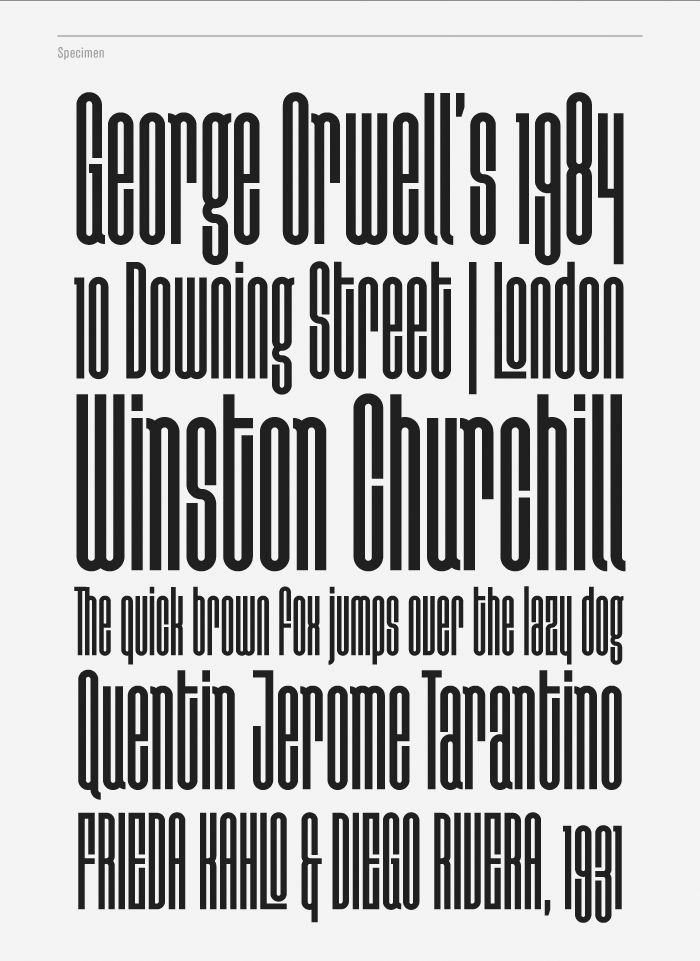
Начнем с довольно распространенного примера — пропорционального изменения размера шрифта. Например, вы используете на своем сайте системный шрифт, но в какой-то момент решаете отказаться от него и купить шрифт, более подходящий под специфику вашей работы. Но вот проблема: вы заменяете на своем сайте системный шрифт на новый, и верстка портится настолько, что можно делать новый макет. Причины могут быть разные, и одна из них заключается в том, что физические размеры этих двух шрифтов могут значительно отличаться.